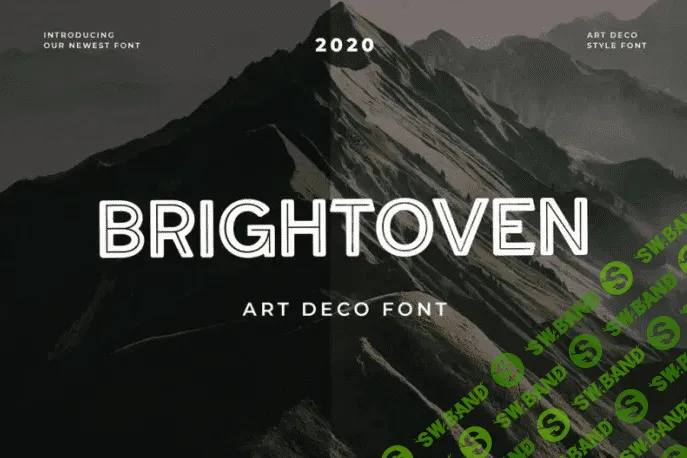
Название: Brightoven Sans Serif Display Font
Представляем наш новый продукт под названием Brightoven Sans Serif Display Font с его уникальными изгибами и врезками, что делает его одним из самых запоминающихся шрифтов с заглавными буквами на рынке. Этот шрифт идеально подходит для модного брендинга или редакционного дизайна и отображает как мужские, так и женские качества. Также вы используете этот шрифт в дизайне логотипов и этикеток, дизайне одежды, музыке, рекламе, футболках, брошюрах и многом другом!